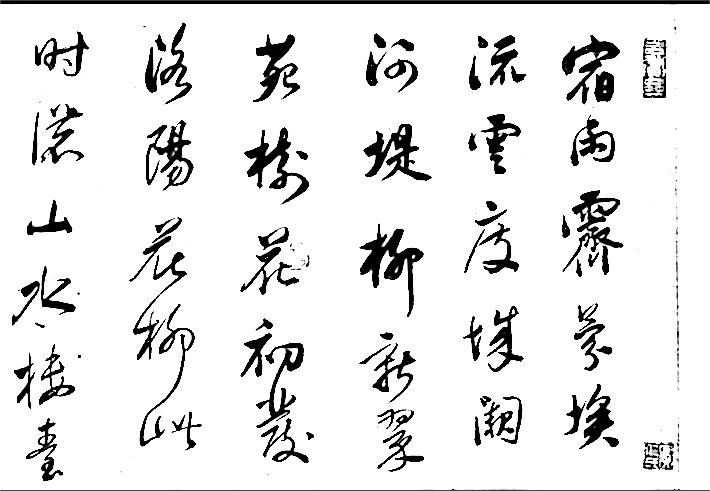
汉标董其昌宋之问诗 By 真迹小字库 商用字体
字体全名: 汉标董其昌宋之问诗
字体简介: 1、下载须知:本字库非标准GB2312字库。本字库只包含了真迹书法原稿中的部分字体。字数的多少取决于原稿的字数的多少。如果有明白的请先联系字觅客服咨询。 2、作品简介:汉标董其昌宋之问诗是一款根据明朝后期大臣、书画家董其昌的经典书法作品《行书宋之问诗》卷,经过再次调整制作的小字库,《行书宋之问诗》卷书写时间为“辛亥寒食次日”,即万历三十九年(1611年),董氏时年57岁。两年前,他辞去福建副使一职,此时在江南以游历山水和书画创作自娱。从他的自题中可知,此卷是以鼠须笔书写,心手相应,颇得己意,并称只恨不能为米芾所赏,可见颇传米书神韵。 3、创作过程说明:汉标董其昌宋之问诗作者根据搜集到的真迹图片,于2022年6月15日开始运用抠图、处理背景图,运用造字软件经过再次调整,增减笔画轮廓及修复笔画缺失,调整书法文字比例结构,把每个文字调整到最佳使用效果,将421个汉字逐字编码代入模板,在2022年7月20日完成小字库制作。 4、独创性说明:汉标董其昌宋之问诗小字库的出现,在全国字库界独树一帜,对于中国古代书法艺术的传承具有划时代意义,并且通过把古代名家书法作品调整字体笔画基本位置,合理布局,提高清晰度,去除笔画边缘毛刺及脏点,纠正错别字,均衡整体文字的大小,再次创作而制作成现代,让更多书法爱好者能够通过电脑打字使用,真正感受到古代名家书法之美。并且也可以在各种场景下应用。